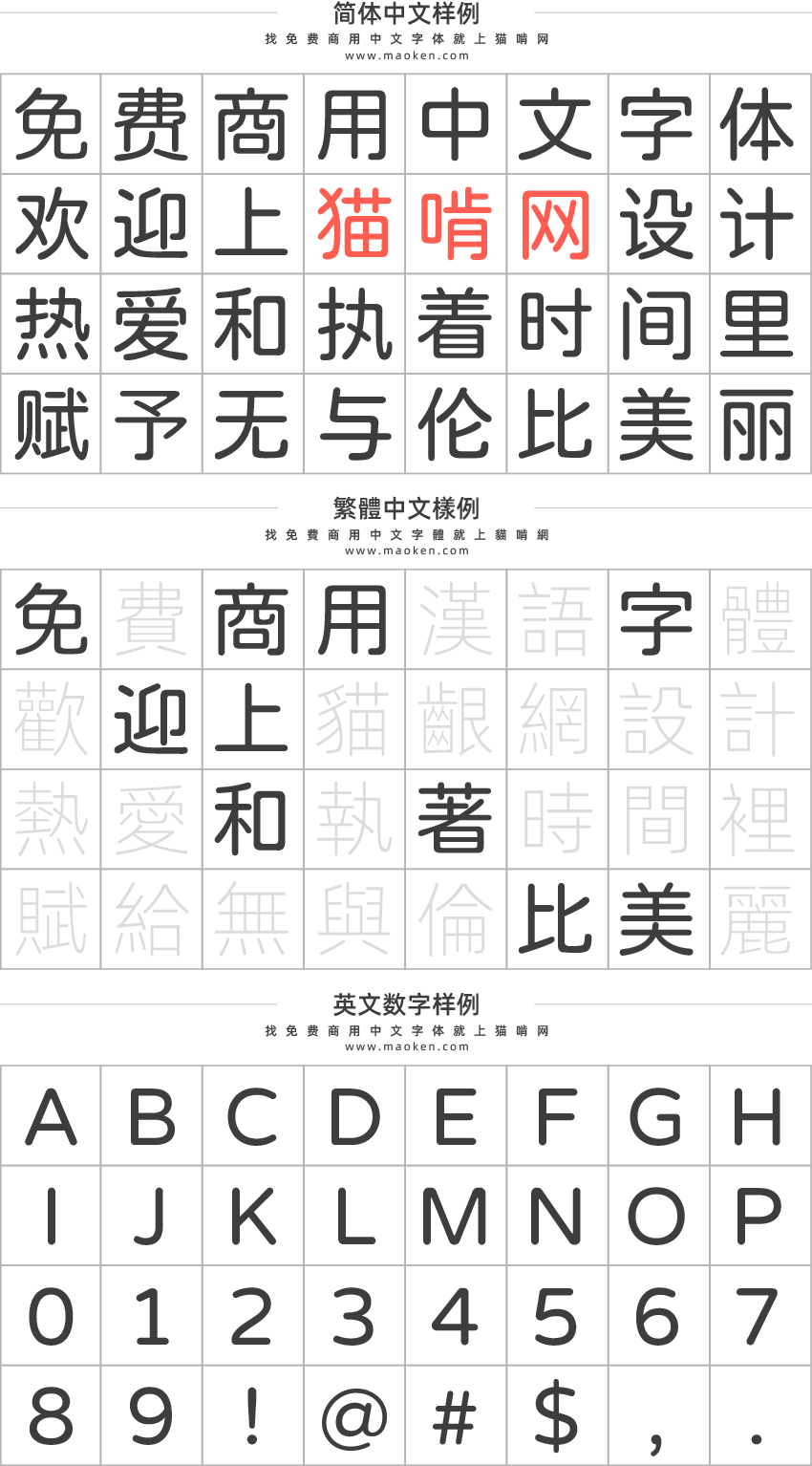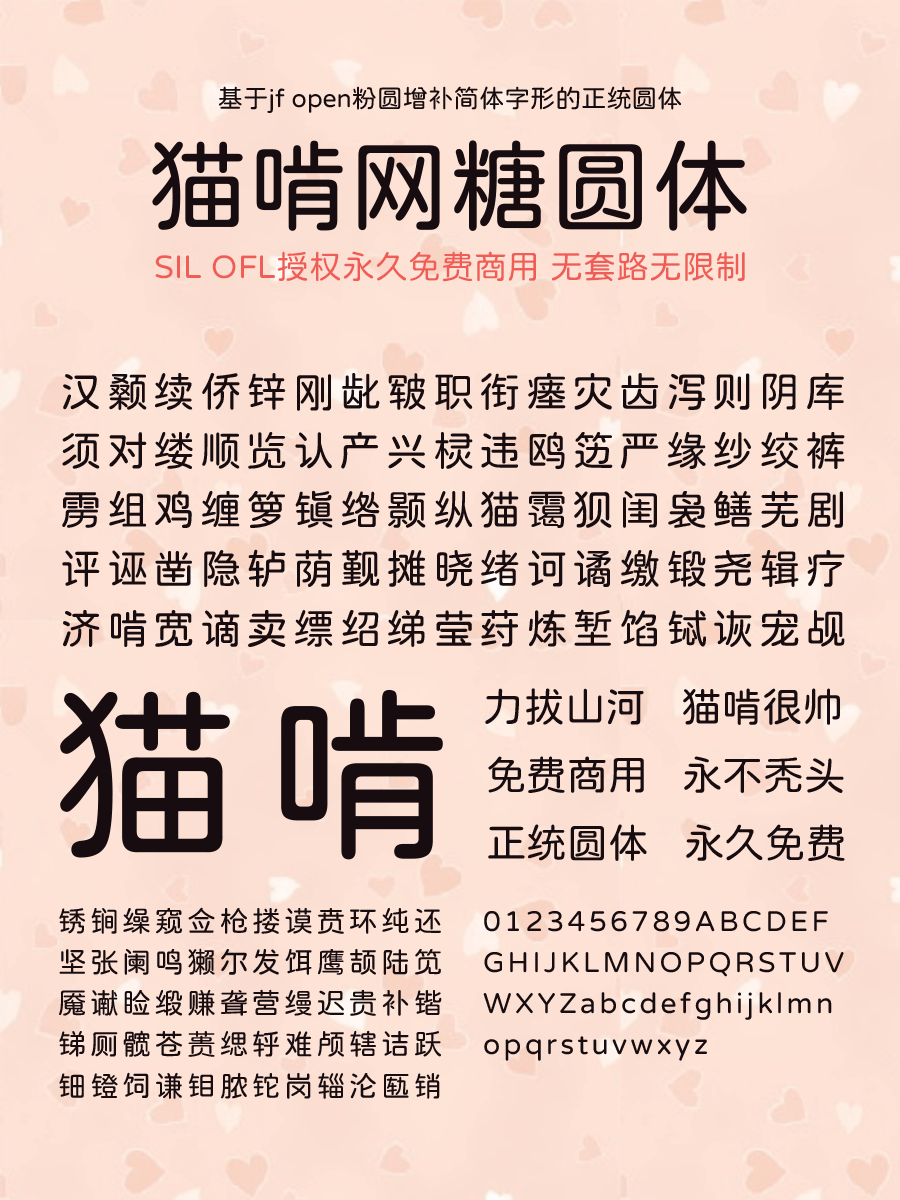
猫啃网糖圆体:国内首款免费商用传统圆体 基于jf open粉圆增补
猫啃网自从上线之后,搜集了国内外近200多款免费商用的中文字体,但是一直感慨的是还没有一款免费商用的圆体字库。现在的圆体字库,很多都是基本于思源黑体通过程序进行改造,把笔画变圆,但是看上去还是很有黑体的感觉。
后来台湾的justfont发布了一款以“小杉圆体”进行修改增补而成的圆体字形“jf open粉圆”,十分受欢迎。但是可惜的是,这款字体以繁体为主,对大陆的小伙伴来说要用起来就十分尴尬,因为简体缺字太多。有感于此,猫啃君开始了“jf open粉圆”的简体增补计划,希望可以基于粉圆字形补全简体字形以方便大陆的小伙伴能愉快地使用该字体。
由于猫啃君并不是专业的字体设计师,对于字库制作更是从零开始,所以“猫啃网糖圆体”的字形上依然存在很多问题。“猫啃网糖圆体”和”传承糖圆体“是猫啃君与马来西亚网友@夜煞之乐(字体统计软件作者)共同完成,在此特别鸣谢@夜煞之乐大力支持与指导。
目前“猫啃网糖圆体”已完成简体GB2312常用汉字的增补,未来计划最终完成增补通用规范汉字表。
目前“猫啃网糖圆体”在保持原字体风格的基础上增补大陆简体字形。
糖圆体将会分为两个版本,一个是“猫啃网糖圆体”,这个版本将会以简体字体为主,在写法上会更贴近中国大陆的简体的习惯写法,现阶段准备发布的测试版本字体中许多字仍是旧字形,这些字将在完成gb2312的汉字后才会一并进行修改。
而另一个版本是”糖圆体旧字形“,这个版本主要由@夜煞之乐进行维护。旧字形版本将会包含简体和繁体的字符集,在字形上以贴近原open粉圆的旧字形为主。另外,该字体也会通过opentype功能提供简体版本的字形进行选择,但是在不支援opentype的软件中仍会显示旧字形。
• 完成GB2312标准6763个汉字。
• 修复了一些字形的错误。
• 调整了一部分字体的比例问题。
Ver 0.11(2020/09/18)
• 新增147个简体中文字。
• 把标点符号修改为简体习惯写法。
Ver 0.10(2020/08/31)
• 猫啃网糖圆体(测试版)正式发布